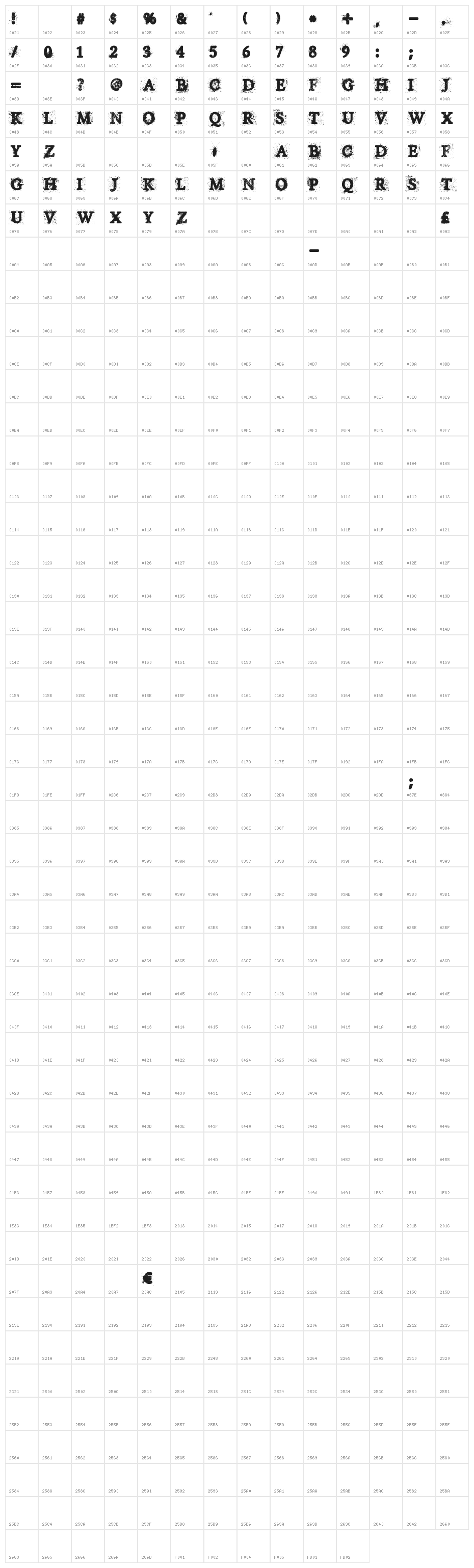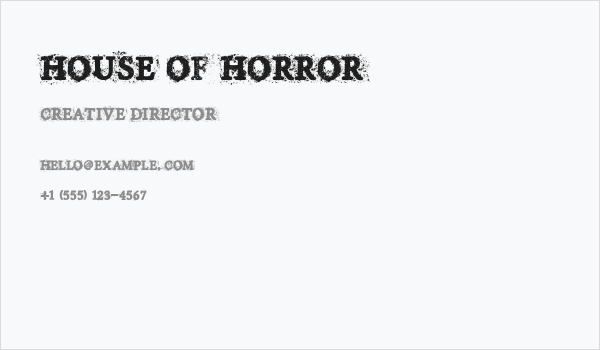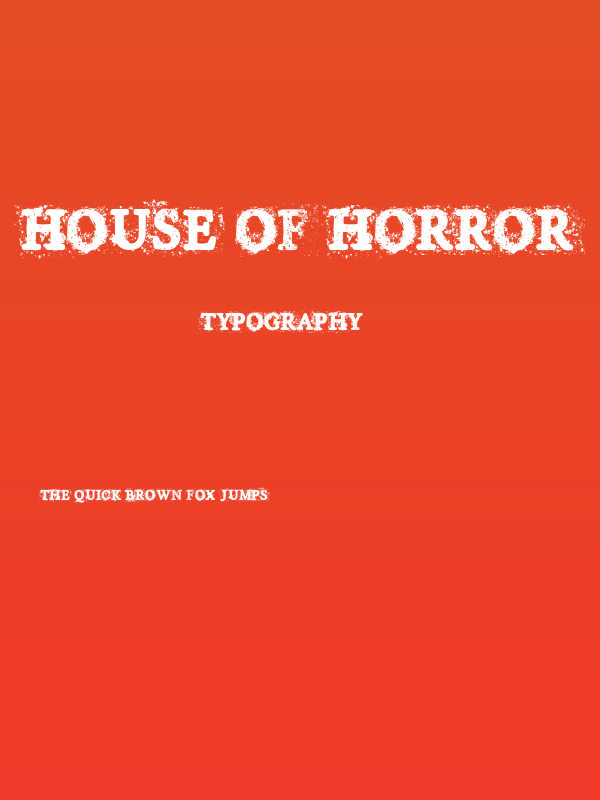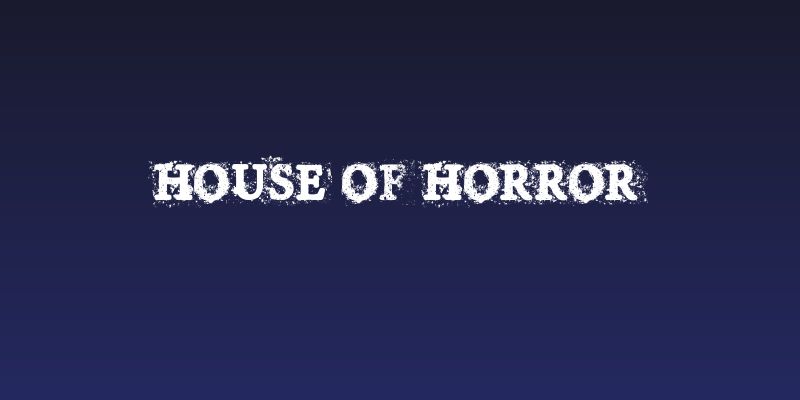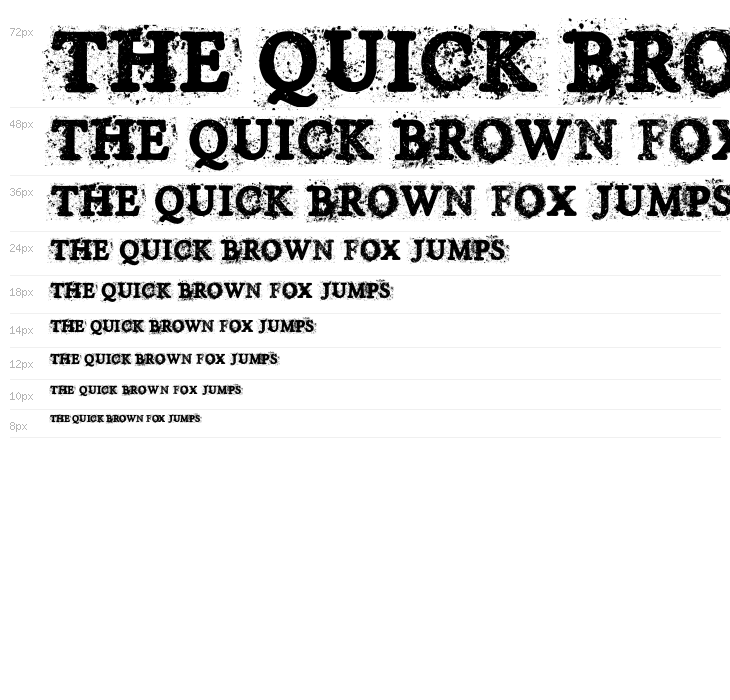
House of Horror Font
| 使用场景 | Headlines, Posters, Logos |
| 推荐项目 | Ideal for horror movie posters, Halloween event flyers, spooky book covers, and themed merchandise. |